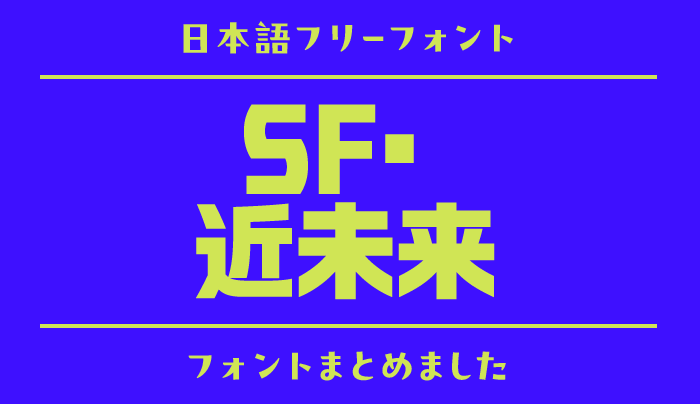
「SF・近未来」の世界観にぴったりな日本語フリーフォント
「SF・近未来」の世界観にぴったりな日本語フリーフォント15選
宇宙船の操作パネル、仮想都市の看板、研究施設の管理番号。SFらしさは背景だけでなく、そこに置かれる文字の形からも伝わります。直線的な文字なら冷たく精密に、ドット文字なら昔の人が思い描いた未来のような空気を作れます。
今回は、フォントラボの中から「SF・近未来」のデザインに取り入れたい15書体を紹介します。シャープなロゴ向けからレトロフューチャーの画面演出まで選びました。文字数の少ない装飾用と、漢字を含む説明用を分けて選ぶのがポイントです。
SF・近未来の日本語フリーフォント
ナイトシェーダーフォント
おすすめの場面SF作品のロゴ/仮想都市の看板/電子音楽のジャケット
細い直線で、まだ見たことのない都市の文字を。
細身の線と記号のような字形が、日常の日本語を少し遠い未来へと変えてくれます。建築物や配線を思わせるビジュアルに短いカナのタイトルを重ねたいときにおすすめ。説明文まで同じ書体にせず、ロゴに絞ると独特の形を見せやすくなります。漢字は別書体との組み合わせが必要です。
Digital Desolation Plus
おすすめの場面サイバー系ゲームの題名/架空端末の見出し/テクノロジー映像
横長の輪郭で、機械的なスピード感を演出。
横方向に広がる文字と鋭い斜線が、画面に緊張感を生みます。カタカナのコードネームや英数字の型番を並べると、未来の機器らしい表情に。横幅を使うため、短い言葉を大きく置く構成が向いています。ひらがな・漢字の文章用ではなく、タイトルや画面内のラベル向けとして選びましょう。
源直ゴシック
おすすめの場面研究施設のサイン/メカ設定資料/漢字を含むSFタイトル
直線的なゴシックで、未来の設備に説得力を。
角の鋭い骨格は、装飾を増やさずに硬質な印象を出したいときに便利です。架空の企業名や施設名を漢字で組んでも、工業的な世界観を保ちやすい書体。細かな図面の脇に置く見出しにもおすすめです。長い説明は通常のゴシック体に任せると、情報の役割がはっきりします。
スミカク
おすすめの場面サイバーパンクの看板/架空企業のロゴ/重工業風ポスター
四角に詰めた字形が、都市の密度を感じさせる。
四角い枠に収まるような窮屈さと、画線の切れ目が特徴です。雑然とした都市や大型機械を扱う作品で、文字自体をグラフィックとして見せたいときに合います。短い施設名や組織名を面として配置すると効果的。漢字は収録範囲が限られるため、固有名詞を先に試し打ちしておきましょう。
機械彫刻用標準書体
おすすめの場面機体の銘板/操作スイッチの表示/宇宙船の室名プレート
現実の工業文字を、未来の小道具へ。
機械彫刻の標準書体をもとにした、実用品らしい線の運びが魅力です。派手なSFロゴより、機器の注意表示や管理番号など「そこに実在しそうな文字」に向いています。装飾書体のタイトルと合わせれば、背景設定に具体性を添えられます。収録漢字は限定されるので、専門用語には確認が必要です。
モノマニアック(Monomaniac)
おすすめの場面近未来家電のロゴ/宇宙ステーションの店舗名/カナの機種名
丸みと縦長の形で、親しみのある未来を。
太さの揃った画線と丸い角が、冷たすぎない機械的な印象を作ります。生活に溶け込んだロボットや、未来の街の店名といった設定におすすめ。縦長の文字をゆとりを持って並べると、独特のリズムが引き立ちます。漢字を含まないため、カナ中心の名前を考える段階から候補にすると使いやすい書体です。
ヤデワのジ
おすすめの場面ロボット作品の題名/大型メカのコード名/SFイベントロゴ
重いパーツを組んだような、力強いカナ文字。
太い直線と角度のついた字形が、メカの装甲を思わせる存在感を生みます。大きなロボットや重機が主役の作品で、タイトルに重量感が欲しいときにおすすめです。長い文章では形が混み合いやすいので、数文字の名前を主役に。漢字なしの収録構成を活かして、カナや英数字で組むと統一感が出ます。
ボトムズG
おすすめの場面廃宇宙船の表示/使い込まれた装備のラベル/荒廃した未来の見出し
かすれた文字で、未来にも経年変化を。
整ったゴシックの骨格に荒れた質感が加わり、新品ではない設備の雰囲気を作れます。清潔な研究施設より、長年稼働した宇宙船や使い込まれた道具の表示に向く書体です。大きめの見出しならかすれが伝わりやすくなります。小さな操作案内には、別の読みやすい書体を組み合わせましょう。
でんきチップ
おすすめの場面レトロSFのタイトル/架空ゲームの起動画面/端末風ビジュアル
太めのドットで、懐かしいコンピュータの未来像に。
ピクセルの輪郭がはっきりしていて、古いゲーム機を思わせるデジタル感を加えられます。最新技術の広告というより、レトロフューチャーの演出におすすめです。日本語の短い指令やタイトルを置くと、画面全体をゲームの世界へ寄せられます。縮小時にはドットがつぶれていないか確認しましょう。
あいこの未来クラブ
おすすめの場面宇宙探索ゲームの会話窓/架空OSの画面/ドット絵の見出し
小さなグリッドから、やわらかなデジタル世界へ。
7×7ピクセルをもとにした小さな字形は、機械的なのに素朴な表情があります。厳しいディストピアより、探索や冒険を楽しむレトロSFと好相性。ドット絵のキャラクターに添える短い会話や、基地内の案内に向いています。画面を拡大して使う場合も、文字と背景のピクセル感を揃えるとまとまります。
しかくふとフォント
おすすめの場面ピクセルSFのタイトル/ゲーム開始画面/ミッション名
極太の四角い文字で、起動画面にインパクトを。
四角いシルエットが強く、画面の中心に大きく置くタイトル用として選びたい書体です。細かいシステム情報より、短い作品名やミッション名を力強く見せるのが得意。無料版の漢字は小学2年生までなので、難しい熟語が必要なときは文字の不足に注意してください。かな中心のタイトルにも向いています。
縁架ドットゴシック24
おすすめの場面情報端末の日本語表示/レトロSFの字幕風画像/システム画面の見出し
ゴシックの骨格を残して、ドット表現に統一。
日本語の形を保ったままデジタルの粒感を取り入れたいときの候補です。端末の見出しと短いメッセージを同じ雰囲気で揃えやすく、漢字を含む画面演出にも使えます。長い説明を小さく詰め込むより、行間を取り、情報を短く分けて配置するのがおすすめです。
VCR-JP